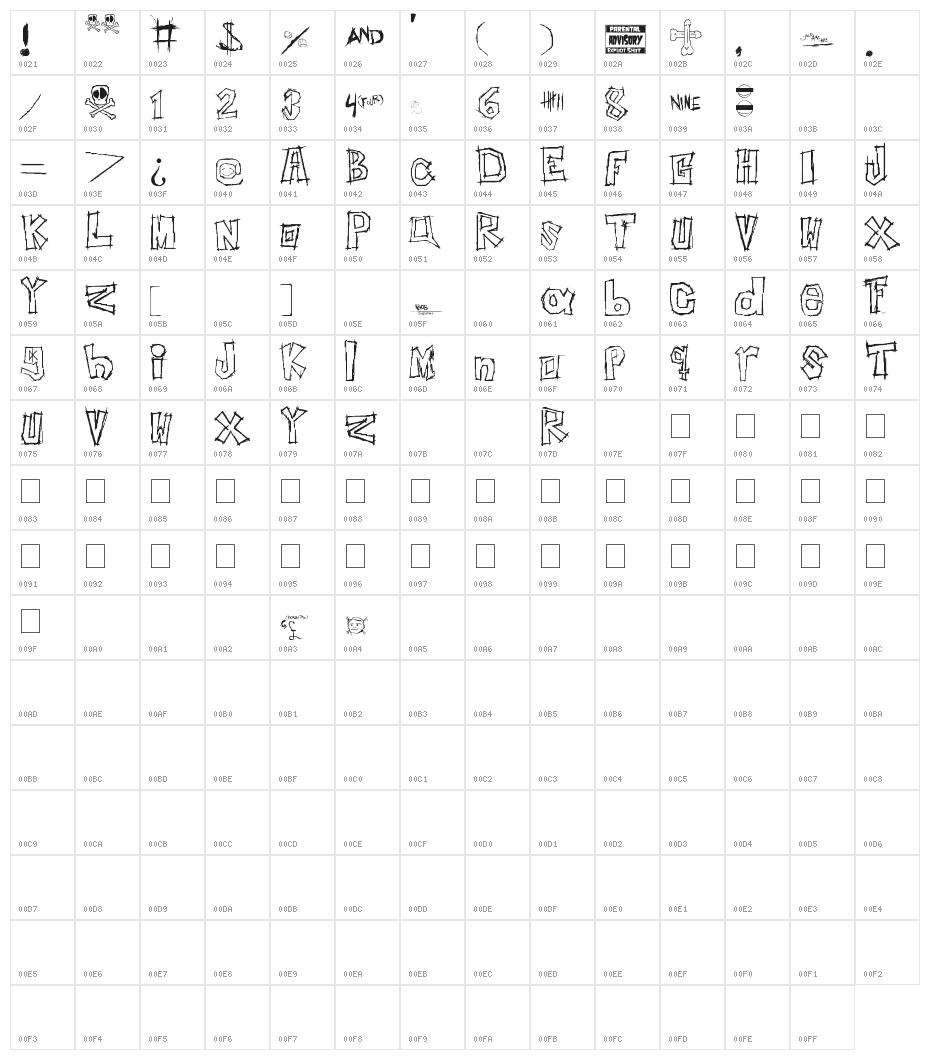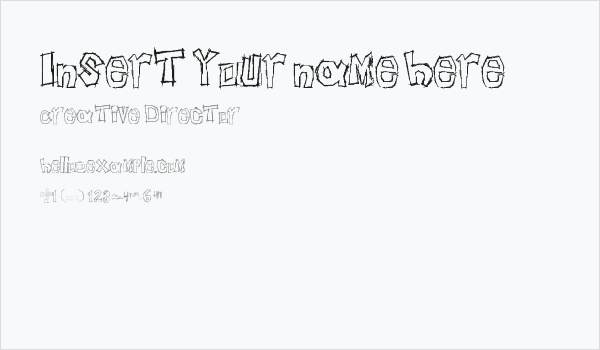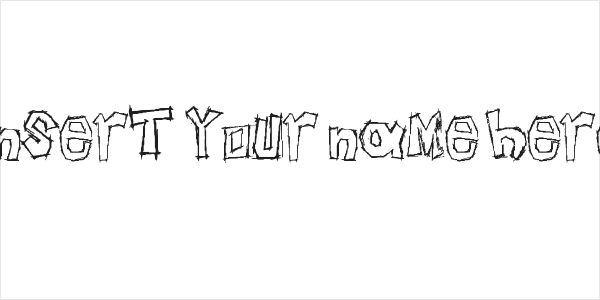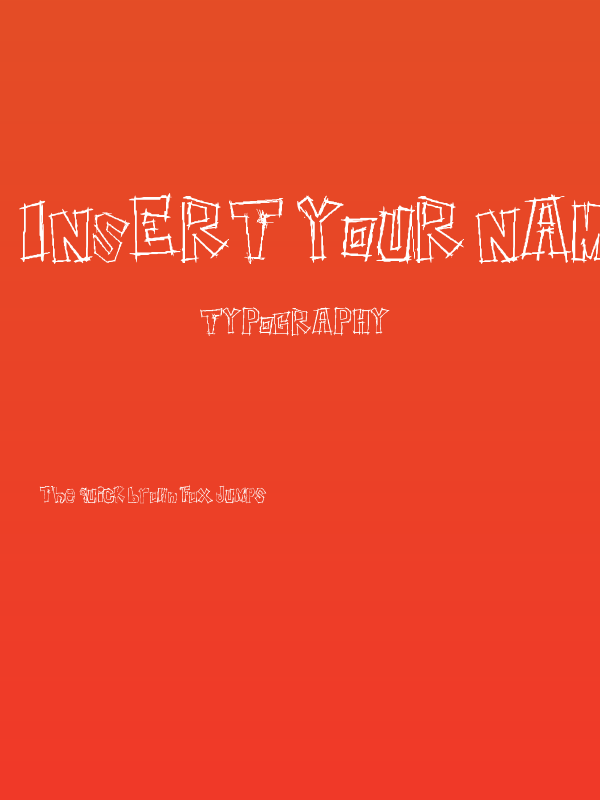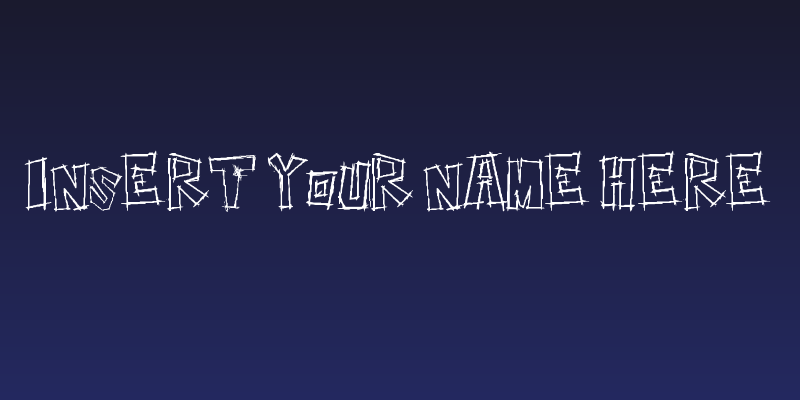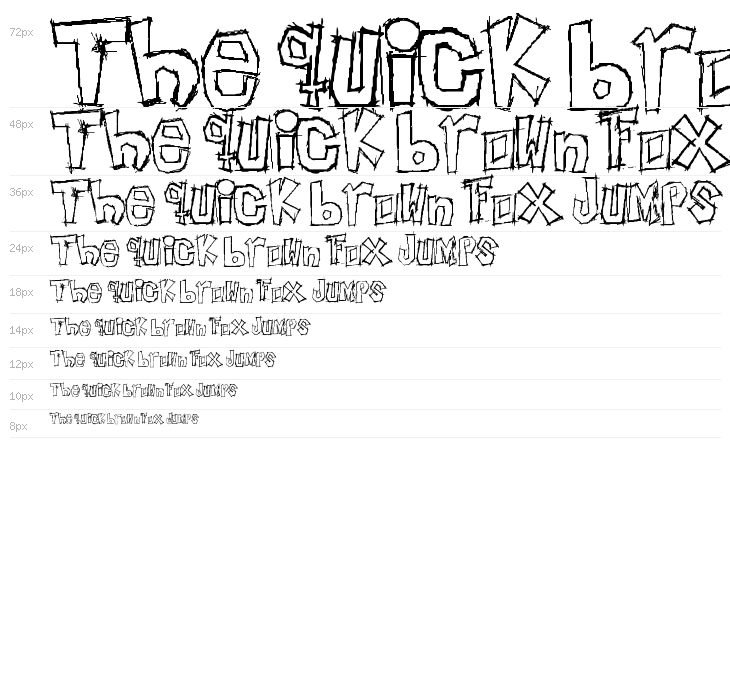
Insert your name here Font
| Caso d'uso | Logos, Posters, Album Covers |
| Progetti proposti | Perfect for album covers, posters, streetwear branding, or any project needing a bold, edgy look. |